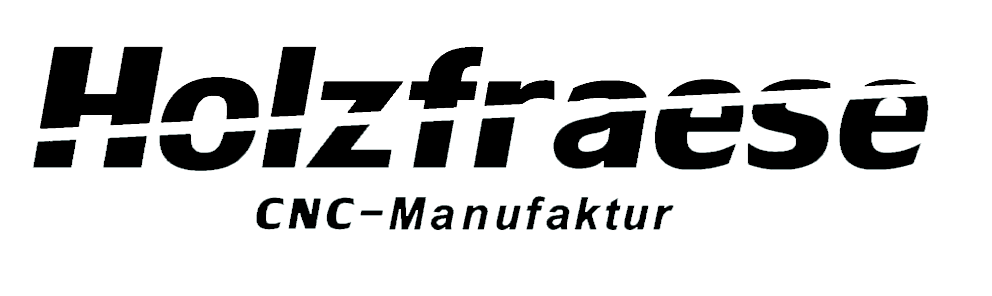
Welche Schrift ist das? (Holzfräse Manufaktur)
ich suche dringend die Schrift, die für den Schriftzug verwendet wurde.
Leider liegt mir nur ein Pixelbild des Schriftzugs vor, der entsprechend vektorisiert werden soll.
Das große Wort „Holzfräse“ könnte eine gekippte Antique Olive Bold sein. Die Bold gibt es ab Werk nicht in windschief. Gleiches gilt für „CNC“. Dass Wort „Manufraktur“ ist wohl eine Arial Italic. Der Bindestrich sollte aus der Arial sein, nicht aus der Antique Olive?
Die Arial Bold Italic stimmt für "–Manufaktur", die Antique Olive Bold für "Holzfräse" leider nicht, auch wenn ich sie kippe.
Die Antique kommt dem gesuchten Font zwar recht nahe, aber trifft die Charakeristik der Schrift nicht ganz (Strichstärke, Endstriche, Punzen).
Mach es halt einfach richtig und besser. Alles in einer Schrift mit ähnlicher Anmutung des Holzfraese-Schriftzugs. (Warum eigentlich nicht Fräse?) Die Schriftmischeung mit Arial ist doch Murks. Kannst du dem Kunden dann auch gleich als qualitativ extrem verbessertes Redisign verkaufen (nur wenn es ihm auffällt und er fragt, warum/ob es leicht anders aussieht).
mit scheint das ist einfach die Verdana in Laufweite und Schräge manuell modifiziert...
leider passen auch die von Dir erwähnten Schriften nicht, gerade am z und am e fallen die Unterschiede auf.
Ich fürchte ich werde den Schriftzug nachbauen müssen…